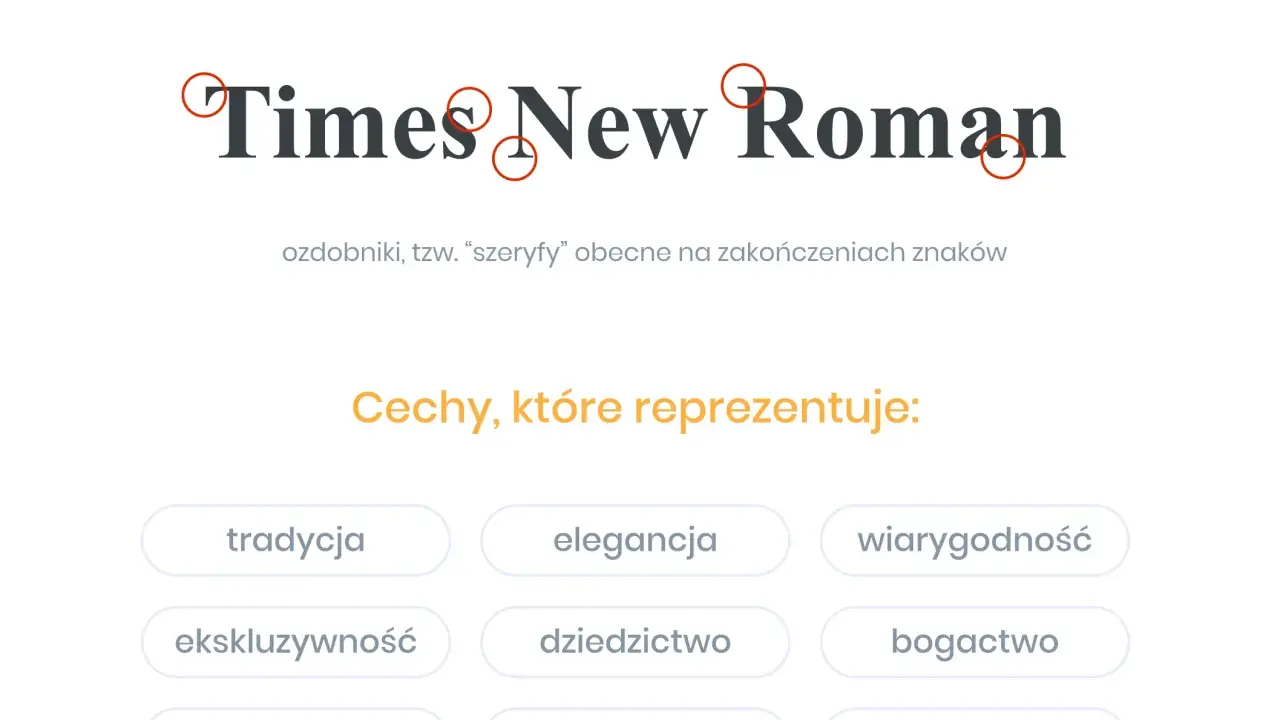
Font szeryfowy potrafi nadać tekstowi klasę, rytm i odrobinę autorytetu, ale tylko wtedy, gdy jest dobrany świadomie. W praktyce liczy się nie sam wygląd liter, lecz to, jak krój pracuje w dłuższym tekście, na ekranie, w druku i w identyfikacji marki. Poniżej rozkładam temat na prostą definicję, zastosowania, odmiany i kryteria wyboru, żeby łatwiej było ocenić, kiedy taki krój naprawdę pomaga, a kiedy tylko ładnie wygląda w podglądzie.
Najważniejsze rzeczy do zapamiętania przed wyborem kroju z szeryfami
- Szeryfy to drobne zakończenia kresek liter, które wpływają na charakter, czytelność i tempo odbioru tekstu.
- Taki krój zwykle dobrze sprawdza się w dłuższych formach, materiałach premium i projektach o bardziej klasycznym tonie.
- Na ekranie nie ma prostego podziału na „dobre” i „złe” kroje, bo dużo zależy od rozmiaru, kontrastu i odstępów.
- Najczęściej spotkasz odmiany old style, transitional, didone i slab serif, a każda daje trochę inny efekt.
- Przy wyborze patrz na polskie znaki, x-height, licencję i test w realnym kontekście, nie tylko na sam podgląd pojedynczych liter.
Czym są kroje szeryfowe i skąd bierze się ich charakter
Szeryfy to niewielkie zakończenia kresek liter, zwykle w formie poprzecznych lub ukośnych dodatków przy końcach znaków. Dzięki nim litery zyskują bardziej zarysowaną strukturę, a cały blok tekstu zaczyna wyglądać spokojniej i bardziej „ułożenie”. Ja traktuję to nie jako ozdobnik dla samej ozdoby, ale jako element, który realnie zmienia tempo czytania i ton komunikatu.
W typografii taki krój nazywa się też antykwą. Historycznie kojarzy się z drukiem, książkami i edytorialem, ale to nie znaczy, że jest zamknięty w papierze. Dobrze zaprojektowany wariant sprawdza się także w cyfrowych publikacjach, o ile nie jest zbyt delikatny, zbyt ciasny albo przeznaczony wyłącznie do dużych nagłówków.
W praktyce najważniejsza lekcja jest prosta: sam fakt obecności szeryfów nie gwarantuje czytelności. O wiele ważniejsze są proporcje liter, kontrast grubości kresek, światło wewnątrz znaków i to, czy krój został pomyślany do tekstu, czy raczej do efektownego użycia w krótkim haśle. To prowadzi już do pytania, w jakich sytuacjach taki wybór rzeczywiście pracuje na projekt.
Gdzie działa najlepiej, a gdzie wymaga ostrożności
Kroje z szeryfami najczęściej wygrywają tam, gdzie tekst ma budować zaufanie, spójność i trochę bardziej redakcyjny charakter. Dobrze wyglądają w magazynach, raportach, książkach, materiałach eksperckich, komunikacji premium i w brandach, które nie chcą brzmieć zbyt technicznie. W marketingu to ważne, bo typografia od razu ustawia oczekiwania odbiorcy wobec treści.
| Kontext użycia | Dlaczego krój z szeryfami działa | Na co uważać |
|---|---|---|
| Długie teksty | Buduje rytm i pomaga prowadzić wzrok przez akapity | Zbyt cienkie odmiany męczą przy małym rozmiarze |
| Branding premium | Dodaje wrażenia tradycji, jakości i stabilności | Łatwo przesadzić i uzyskać efekt ciężki albo „stary” |
| Logo i nagłówki | Może dać wyraźny charakter i wyróżnienie | Wymaga dopracowanych odstępów i czasem indywidualnych korekt |
| Interfejsy i mobile | Dobrze zaprojektowany krój potrafi wyglądać bardzo elegancko | Mały ekran bez odpowiednich proporcji szybko obnaża słabe detale |
Ja zwykle nie pytam najpierw, czy krój jest szeryfowy, tylko gdzie będzie żył tekst. Jeśli ma działać w długim czytaniu, w druku lub w materiale eksperckim, taki wybór często ma sens. Jeśli jednak projekt opiera się na miniaturowych opisach, ciasnym layoutcie i dużej liczbie informacji w małej przestrzeni, trzeba sprawdzać każdy detal z większą ostrożnością. Następny krok to rozpoznanie samych odmian, bo „szeryfowy” to dopiero punkt wyjścia.
Najważniejsze odmiany, które warto rozpoznawać
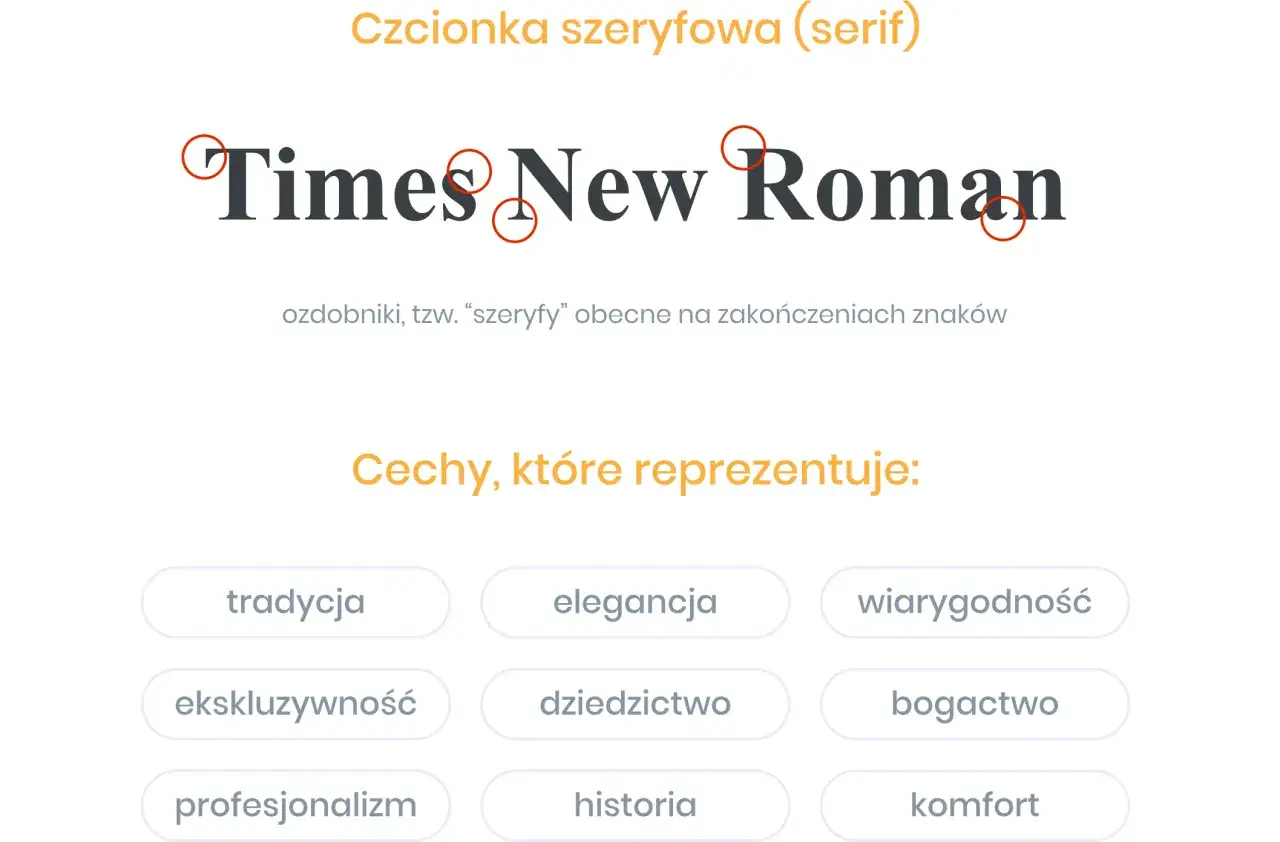
Nie każdy krój z szeryfami daje ten sam efekt. Jedne wyglądają miękko i literacko, inne bardziej elegancko i kontrastowo, a jeszcze inne są masywne i wyraźne. To ważne, bo w projektach marketingowych jeden wybór może komunikować tradycję, a drugi nowoczesny luksus albo solidność.
| Odmiana | Cechy charakterystyczne | Najlepsze zastosowanie |
|---|---|---|
| Old style | Niższy kontrast, łagodniejsze kształty, bardziej humanistyczny rytm | Dłuższe teksty, publikacje redakcyjne, treści o spokojnym tonie |
| Transitional | Wyraźniejszy kontrast i bardziej uporządkowana konstrukcja | Książki, raporty, materiały, które mają wyglądać klasycznie, ale nie muzealnie |
| Didone | Bardzo duży kontrast między grubymi i cienkimi liniami | Luksusowe marki, nagłówki, kreacje modowe, krótkie ekspozycje |
| Slab serif | Mocne, belkowe szeryfy i bardziej „konstrukcyjny” charakter | Logotypy, plakaty, komunikacja z wyraźnym akcentem wizualnym |
W praktyce najwięcej projektów wygrywa nie najbardziej efektowny, ale najbardziej adekwatny wariant. Na przykład Bodoni czy Didot mogą wyglądać świetnie w dużym nagłówku, ale w małym tekście szybko tracą siłę. Z kolei Garamond, Baskerville czy Sabon dają bardziej redakcyjny, „czytający się” efekt, choć bez spektakularnego błysku. Jeśli wybierasz krój do projektu, ta różnica jest ważniejsza niż nazwa samej rodziny.
Jak dobrać krój do projektu bez zgadywania
Najlepszy proces wyboru zaczynam od medium, a dopiero potem patrzę na estetykę. Inaczej dobiera się krój do książki, inaczej do landing page’a, a jeszcze inaczej do opakowania albo logotypu. W typografii często przydaje się też kilka terminów technicznych: x-height to wysokość małych liter bez wydłużeń, interlinia to odstęp między wierszami, a kerning to ręczna korekta odstępu między konkretnymi parami liter.
- Sprawdź zastosowanie - jeśli tekst ma być długi, szukaj kroju z dobrą czytelnością w małym i średnim stopniu pisma.
- Oceń kontrast - im większa różnica między grubymi i cienkimi liniami, tym ostrożniej trzeba podchodzić do małych rozmiarów.
- Przetestuj polskie znaki - ą, ę, ł, ś, ć, ź i ż potrafią od razu pokazać, czy krój jest naprawdę dopracowany.
- Zrób próbę w realnym layoucie - ten sam krój inaczej wygląda w pojedynczym słowie, a inaczej w akapicie i w całej kolumnie.
- Dobierz właściwą wagę - cienka odmiana może wyglądać szlachetnie, ale nie zawsze jest praktyczna.
- Sprawdź licencję - przy pracy komercyjnej to nie detal, tylko część decyzji projektowej.
Ja często dorzucam jeszcze jeden test: wydruk albo podgląd na realnym urządzeniu. To, co wygląda dobrze w bibliotece fontów, nie zawsze dobrze zachowuje się w systemie, przeglądarce czy aplikacji do składu. Ten test szybko pokazuje, czy krój naprawdę pracuje z układem, czy tylko dobrze prezentuje się jako pojedyncza próbka.
Najczęstsze błędy, które psują nawet dobry wybór
Największy błąd widzę wtedy, gdy ktoś wybiera krój tylko dlatego, że wygląda „elegancko” w pojedynczym napisie. Typografia nie działa jak obrazek na Instagramie. Musi pracować z treścią, hierarchią i przestrzenią. Dobrze dobrany krój szeryfowy potrafi pomóc, ale źle użyty szybko robi się ciężki, teatralny albo po prostu mało czytelny.
- Zbyt cienki krój do małego tekstu - cienkie linie znikają, szczególnie na gorszych ekranach i przy słabszym druku.
- Za mała interlinia - wiersze zaczynają się optycznie kleić i tekst traci oddech.
- Przesadne mieszanie stylów - łączenie kilku charakterów naraz daje chaos zamiast kontrastu.
- Ignorowanie światła wewnątrz liter - małe oczka i ciasne formy szybko obniżają komfort czytania.
- Brak testu w polskich znakach - krój może świetnie wyglądać po angielsku, a w polskim składzie wypaść słabo.
- Mylenie elegancji z ozdobnością - nie każdy dekoracyjny detal wzmacnia markę; czasem tylko odciąga uwagę od treści.
W projektach marketingowych to szczególnie ważne, bo typografia ma wspierać przekaz, a nie konkurować z nim. Jeśli odbiorca musi się wysilać, żeby przeczytać tekst, żaden „prestiż” nie pomoże. Lepiej wybrać krój odrobinę spokojniejszy, ale stabilny w użyciu, niż efektowną rodzinę, która psuje całą resztę.
Co sprawdzam na końcu, zanim uznam projekt za domknięty
Na finiszu patrzę już nie na sam krój, tylko na jego zachowanie w całości projektu. Sprawdzam hierarchię nagłówków, odstępy między blokami, kontrast z tłem i to, czy tekst brzmi równie dobrze w wersji szerokiej, wąskiej i mobilnej. W 2026 szczególnie dobrze bronią się projekty, które nie próbują udawać „nowoczesności” za wszelką cenę, tylko po prostu są czytelne, konsekwentne i dobrze osadzone w kontekście.
- Jeśli tekst jest długi, czy wiersze prowadzą wzrok płynnie, bez zmęczenia po kilku akapitach?
- Jeśli krój ma być premium, czy faktycznie podnosi jakość odbioru, a nie tylko ją sugeruje?
- Jeśli ma działać cyfrowo, czy zachowuje klarowność na małym ekranie i przy różnych gęstościach pikseli?
- Jeśli ma pracować w marce, czy wspiera jej ton głosu i nie wchodzi w konflikt z resztą identyfikacji?
To właśnie ten etap najczęściej odróżnia poprawny wybór od dobrego. Dobry krój z szeryfami nie krzyczy o sobie, tylko porządkuje treść i wzmacnia jej sens. Gdy spełnia te warunki, typografia zaczyna robić dokładnie to, do czego została stworzona: prowadzić czytelnika bez zbędnego hałasu.